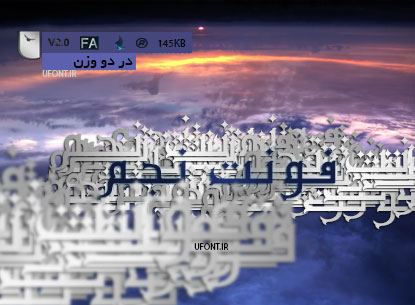
فونت فارسی نجم
فونت فارسی نجم ، فونت ساده و زیبای فارسی مناسب طراحی گرافیک ، این فونت در عین سادگی ساختاری متفاوت دارد ، تغییرات منطقی حروف در جهت متفاوت شدن از سایر فونت ها سبب شده است که این فونت در نوشتار کاملا خوانا باشد و جزو تاپ فونت های یوفونت قرار بگیرد 🙂